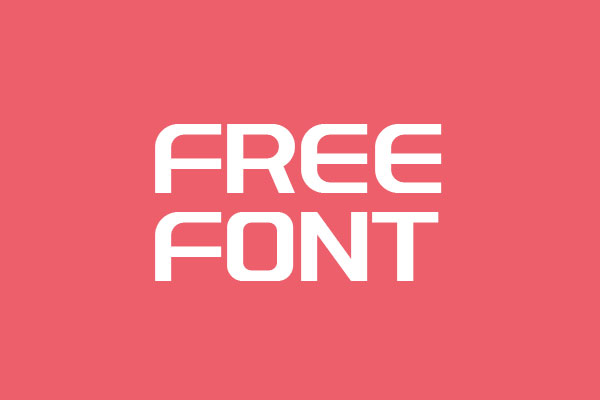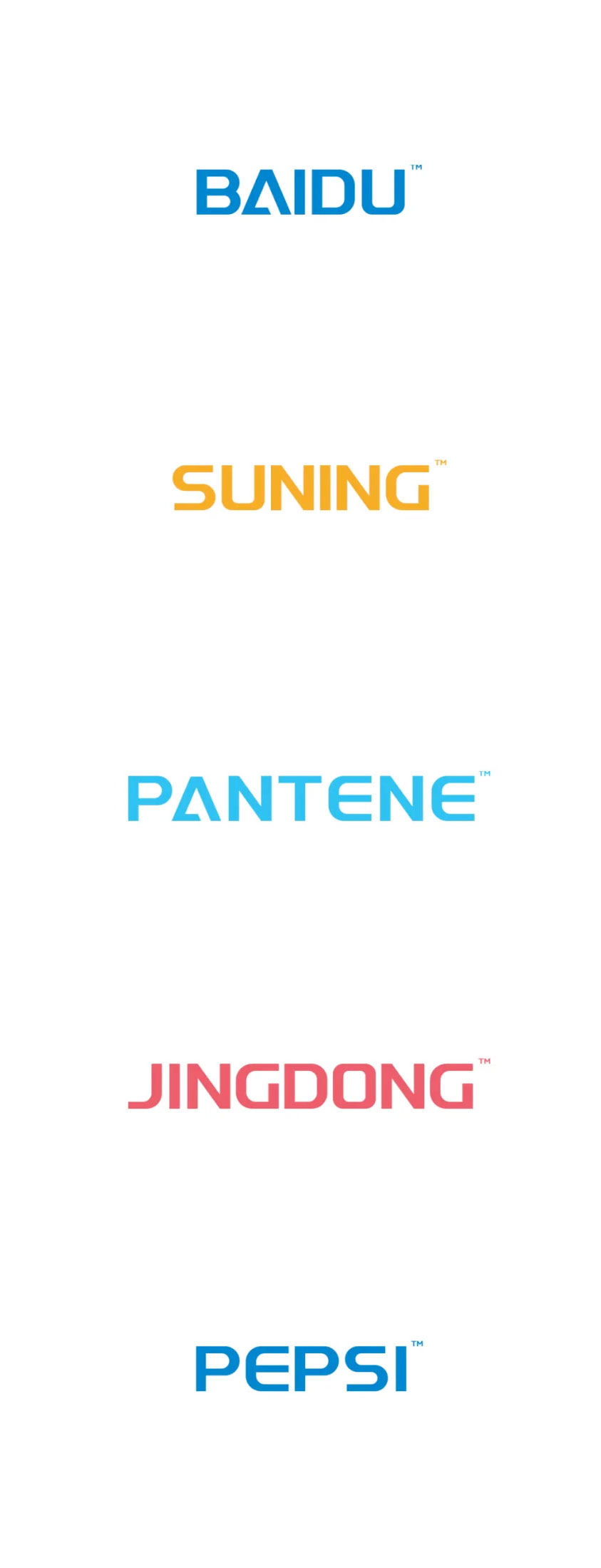
字体圈欣意LOGO体是一款由国内字体设计师邹乐伟创作的英文字库,适用于标题、LOGO设计等场合。它包含52个英文和10个数字,几个标点符号。无论是互联网公司、服装品牌、玩具公司、食品公司还是大型企业,这款字体都非常适合。
这套字体的巧妙之处在于,如果你需要为公司设计LOGO但不会做LOGO设计,你可以直接将字打出来,调整一下间距和颜色,就能让设计国际化。